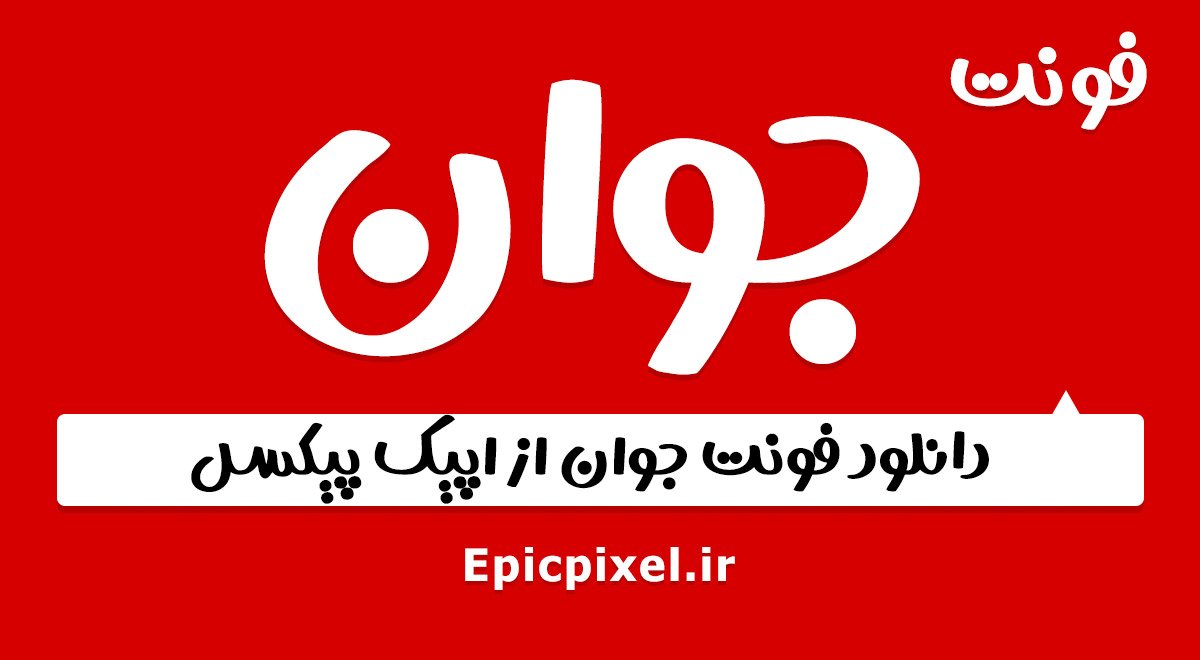
دانلود مجموعه کامل فونت Javan فارسی Font اپیک جوان |
| ⭐ مجموعه فونت | دانلود فونت فارسی اپیک جوان لایت Font Epic Javan Light فونت اپیک جوان ریگولار Epic Javan Regular جوان مدیوم Epic Javan Medium |
| ⭐ توضیحات | مجموعه ای کامل از فونت های جوان و نسخه شبیه سازی شده بنام اپیک جوان فونت اپیک جوان با پشتیبانی از حروف فارسی ، انگلیسی / لاتین ، اعداد فارسی Fu Num بهمراه نسخه وب دارای تعداد زیادی حروف متغییر که با استفاده از ءء بعد از حروف قابل استفاده میباشد |
استفاده از خط های مدور و دایهر ای شکل توی این فونت واقعا حس پویایی خاصی داده که باعث میشه شادابی و جوانی القا بشه ممنونم از سایت خوبتون برای انتخاب فونت های بی نقصی مثل فونت جوان